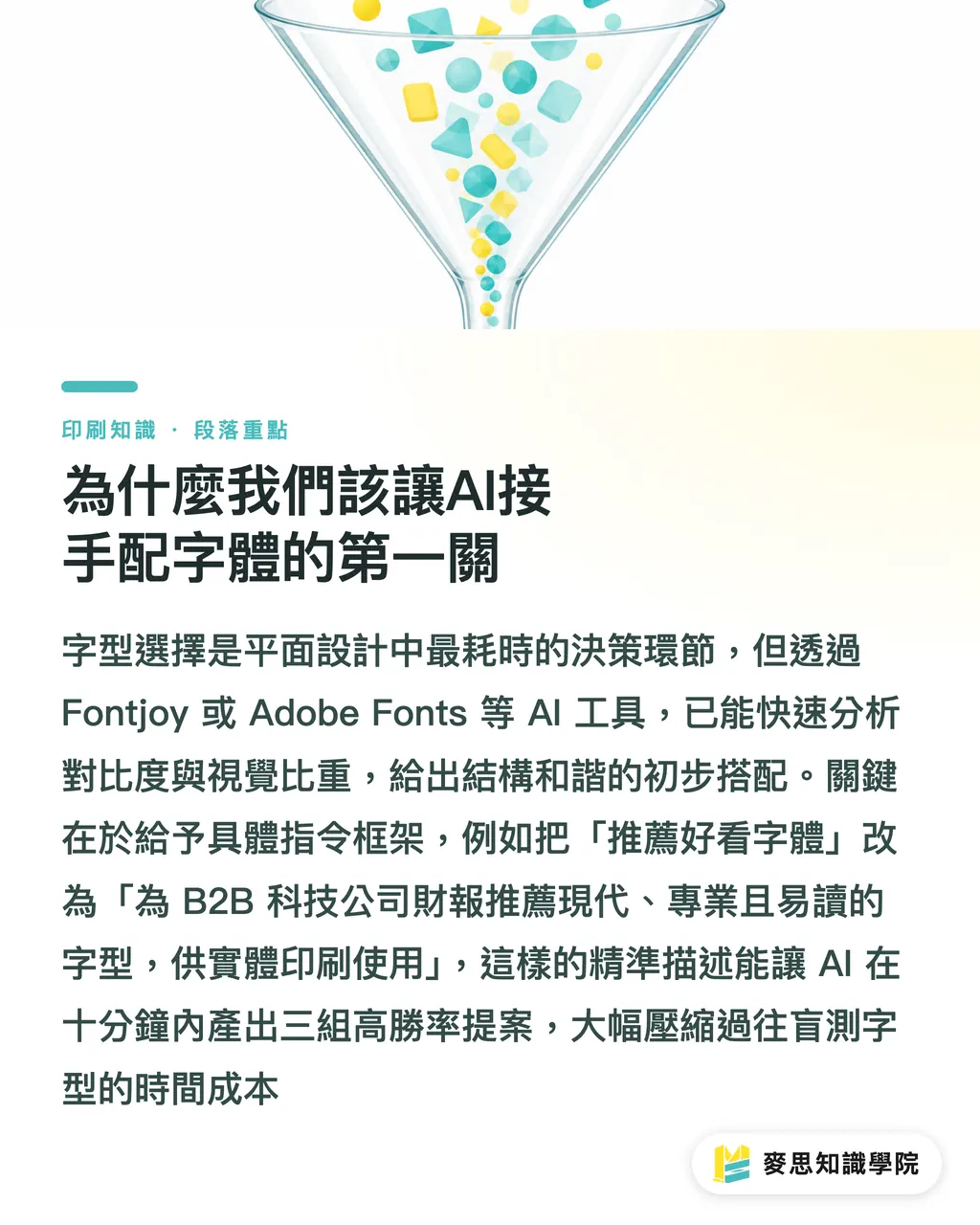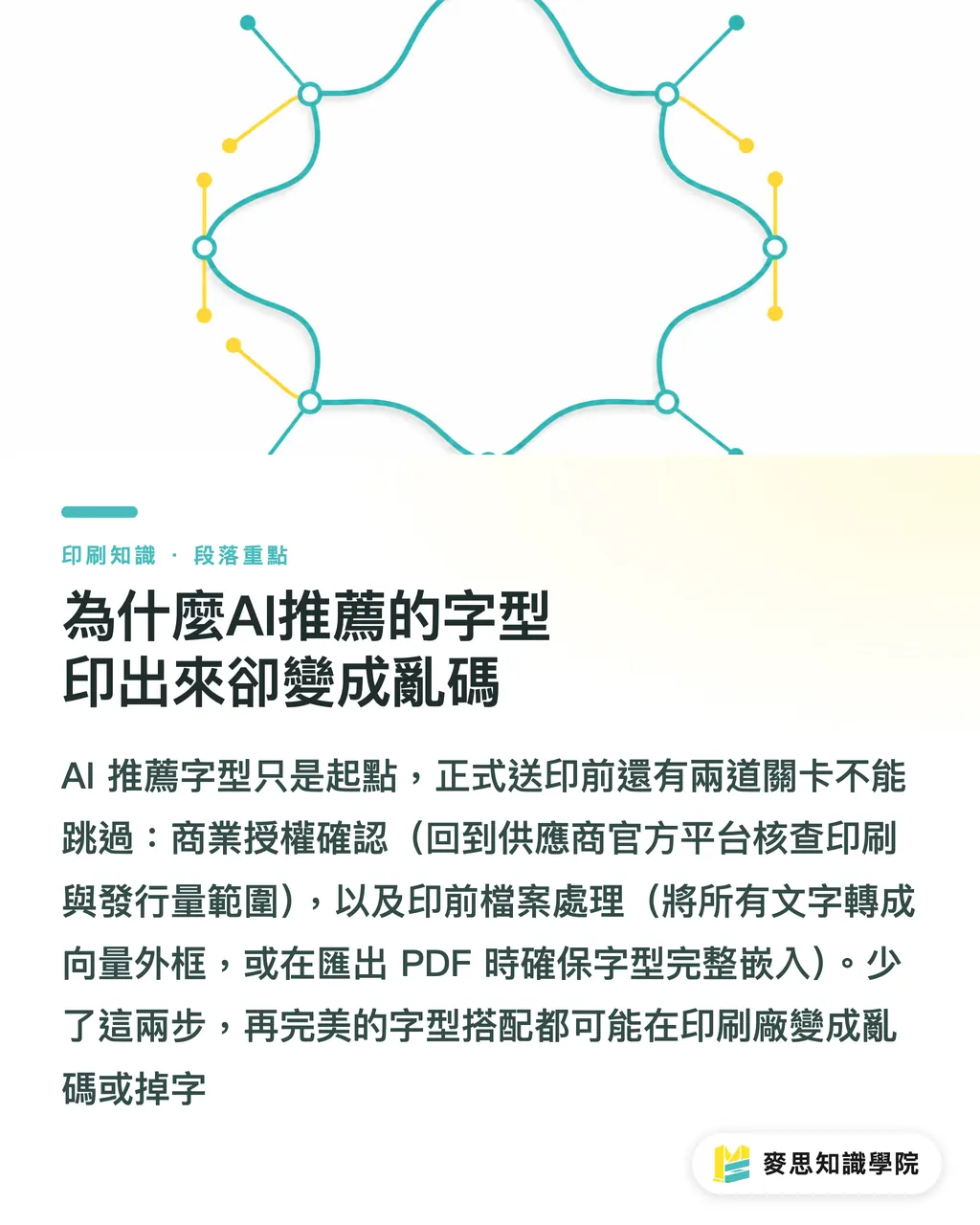
AI配字體指南:印刷顧問教你告別憑感覺的字型搭配術
字型選擇一直是平面設計中最耗時、最容易陷入選擇障礙的環節 這篇文章我將從十多年的印刷實務出發,帶你把字型搭配的專業直覺轉化為AI可執行的系統化流程 從AI工具推薦、中文字體特殊考量到印前輸出檢查,確保你的設計不只在螢幕上好看,印出來更是精準到位
為什麼我們該讓AI接手配字體的第一關
字型選擇往往是整個平面設計中最耗時的決策環節
從我最近接觸的客戶與案子來看,把AI當成初期發想的創意助理,能省下極大的試錯成本
像 Fontjoy 或是 Adobe Fonts 的 AI 推薦功能,已經能透過分析對比度與視覺比重,快速給出一組結構和諧的基礎搭配
要讓AI給出精準建議,關鍵在於給予明確的指令框架
你在描述需求時,必須具體設定品牌個性、使用場合與目標受眾
・把「推薦一個好看的字體」改成「為B2B科技公司年度財報推薦現代感、專業且易讀的字型」
・標明最終媒介是實體印刷品,這會影響字體粗細與字腔大小的推薦傾向
這樣的系統化指令,能把過往需要盲測字型的時間,壓縮到十分鐘內產出三組高勝率提案
為什麼中文字型搭配不能完全照搬AI建議
中文字體有其獨特的方塊結構與排版邏輯,不能單純套用英文字體的機器分析結果
以我處理過上千件印刷案的經驗來看,好的中文排版極度講究視覺節奏
目前多數AI推薦工具仍以拉丁字母為主,若直接套用在繁體中文上,常出現風格互斥的狀況
實務上最穩定的中文搭配法則,依然是傳統的「標題黑體搭配內文明體」
・標題黑體:提供強烈的視覺抓力與現代感,適合快速傳遞核心訊息
・內文明體:藉由橫細直粗的筆畫特性,在長篇閱讀時形成引導視線的水平動線
這套法則結合AI的初步篩選,能讓你快速找到既有新鮮感又不失閱讀性的中文字型組合
印刷實務:反白文字與最小字級的致命傷在哪裡
別再把螢幕上看起來清晰的字體,直接丟去製版印刷
就像AI生成的圖稿容易發生色偏與細節丟失,字體在紙張上的表現也受制於物理條件
印刷最小字級的設定,必須看紙張塗布狀態與印刷方式來決定
如果是模造紙這類吸墨性強的無塗布紙,字級抓太小或筆畫太細,墨水一暈開字就糊了
另一個設計師常踩的坑是深底白字的反白文字
・絕對不要用細明體做反白:明體的橫筆畫非常細,印刷時周圍油墨容易擴張把細線吃掉
・改用中等粗細的黑體或圓體:保持筆畫粗細一致,確保在紙張上能留下足夠的空白面積
我通常會建議客戶,反白文字在未塗布紙上最好維持在 6pt 以上,才能確保印出來不是一場災難
為什麼AI推薦的字型印出來卻變成亂碼
AI工具推薦給你一組完美的字體,不代表你真的能合法且順利地把它印出來
首先是商業授權問題,AI推薦的字庫來源可能包含僅限個人使用的字型
使用前務必回到供應商的官方平台,確認授權範圍是否涵蓋商業印刷與你的發行量
其次是印前檔案處理,這是許多新手最容易忽略的環節
為了確保設計巧思能完美落地,輸出給印刷廠前請務必執行以下檢查
・確實將所有文字建立外框(轉外框):把文字屬性轉為向量圖形,徹底解決跨電腦掉字風險
・仔細檢查是否有漏掉未轉外框的隱藏圖層或孤立文字節點
・若文件性質不適合全轉外框(如多頁手冊),匯出PDF時務必確認字型已完整嵌入檔案中
重點整理
・AI配字體的價值在於加速前期的系統化篩選,而非盲目取代人類設計師的排版直覺
・中文排版依然要回歸「黑體標題、明體內文」的視覺節奏,才能確保長篇閱讀的舒適度
・螢幕清晰度是騙人的,紙張塗布特性與印刷方式決定了最小字級與反白字的成敗
・確實執行文字轉外框與確認商用授權,是保護設計心血與避免印前糾紛的最後防線
延伸思考
FAQ / 常見問題
AI推薦的字體都可以直接用於商業印刷嗎
不行,AI只負責視覺搭配,不保證授權狀態,必須自行前往字型原廠網站確認是否開放商業印刷使用
為什麼我設定了細明體反白,印出來字卻不見了
細明體的橫向筆畫過細,印刷時周圍深色油墨擴張會蓋過細線,反白字應改用筆畫粗細均勻的黑體
中文設計能完全依賴AI字體工具嗎
目前多數AI工具仍以拉丁字母為基礎,中文字體仍需設計師手動把關標題與內文的視覺節奏與易讀性